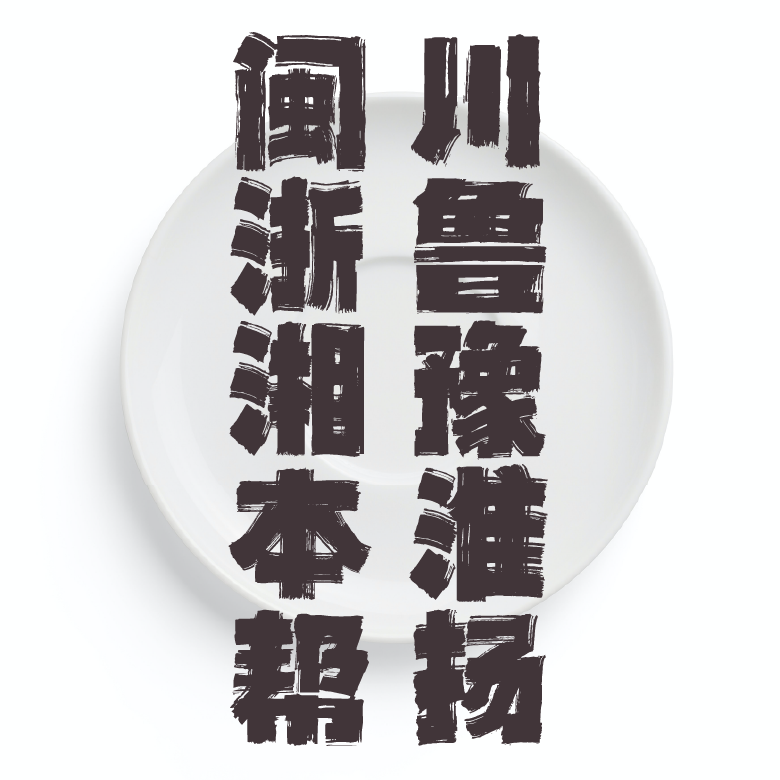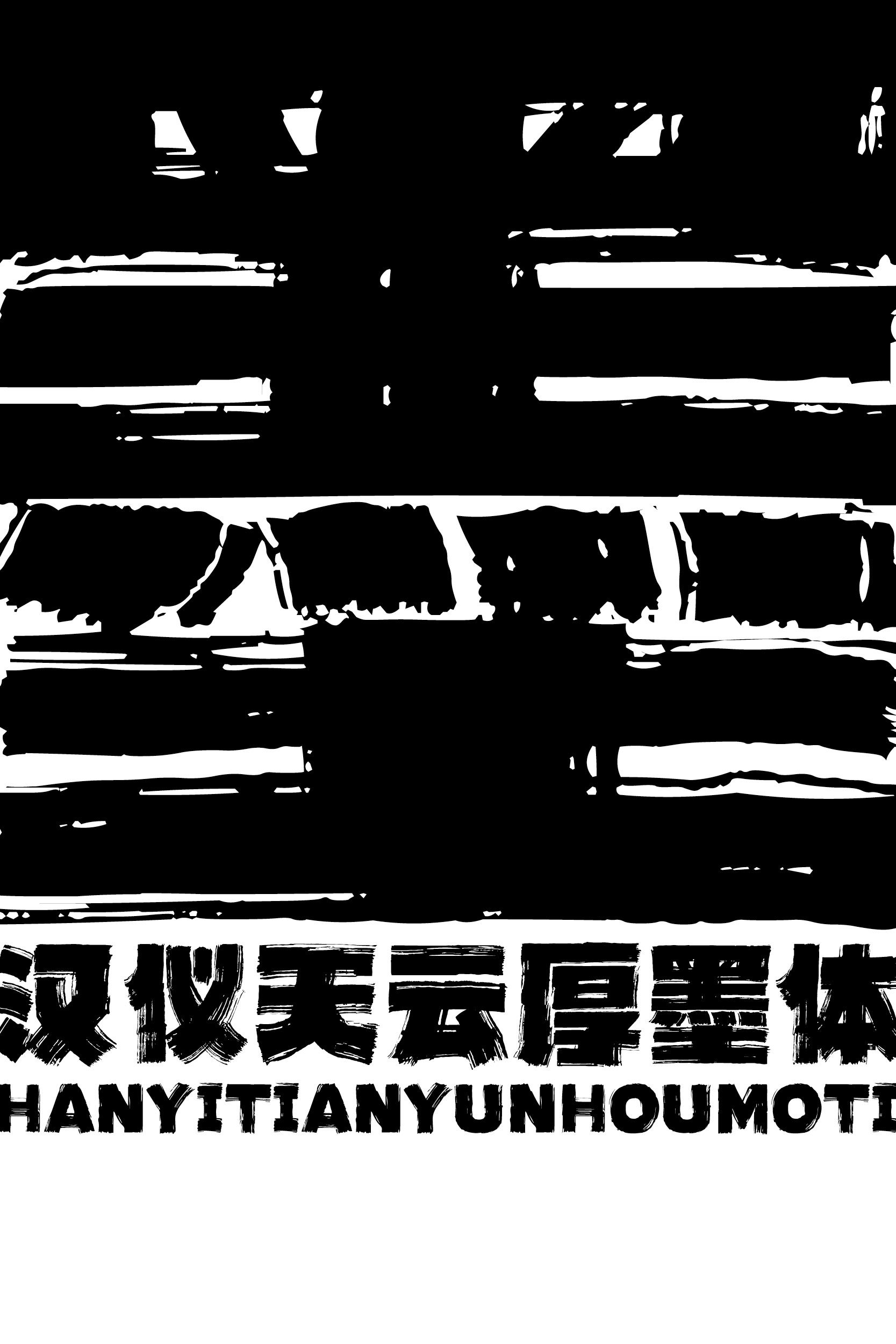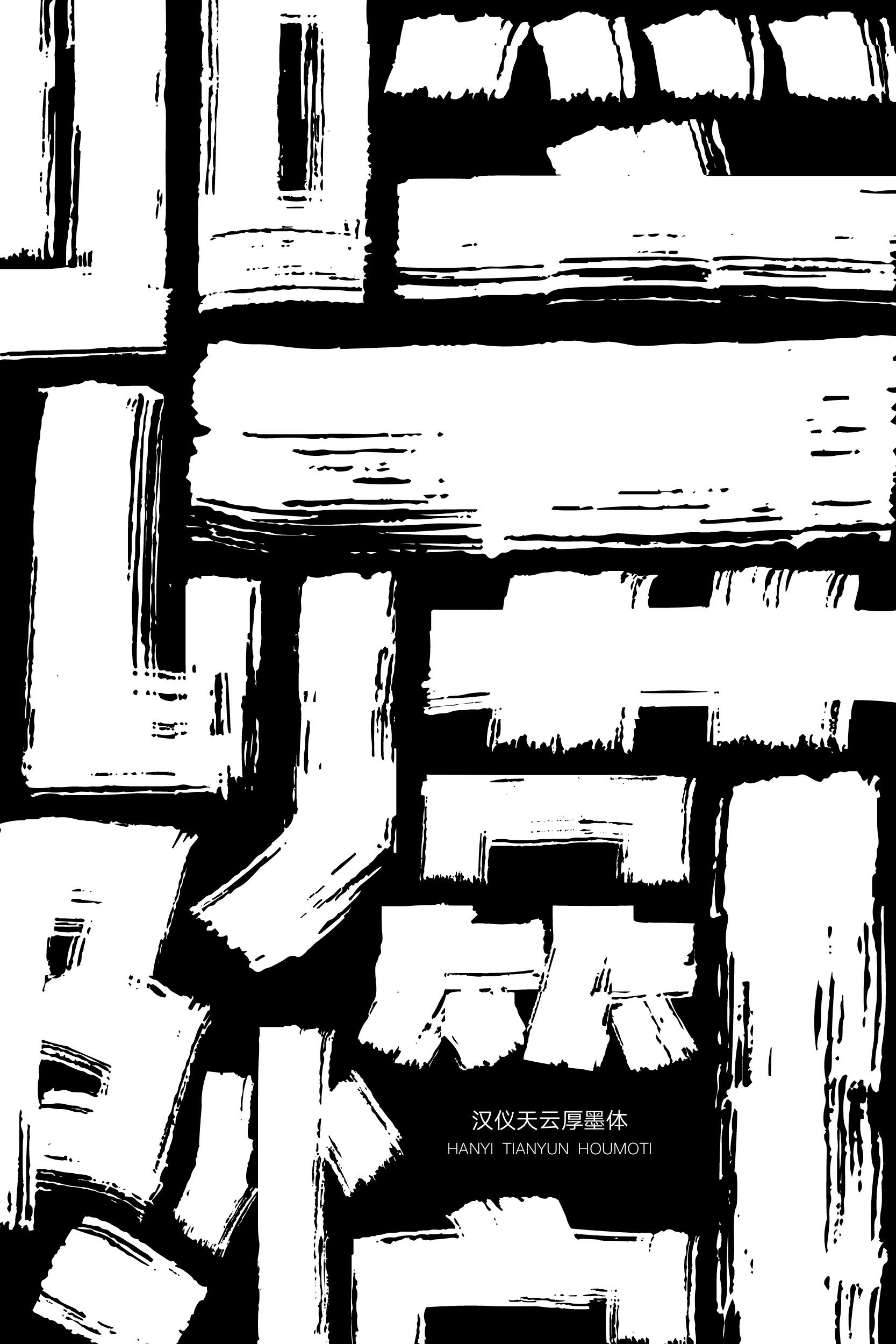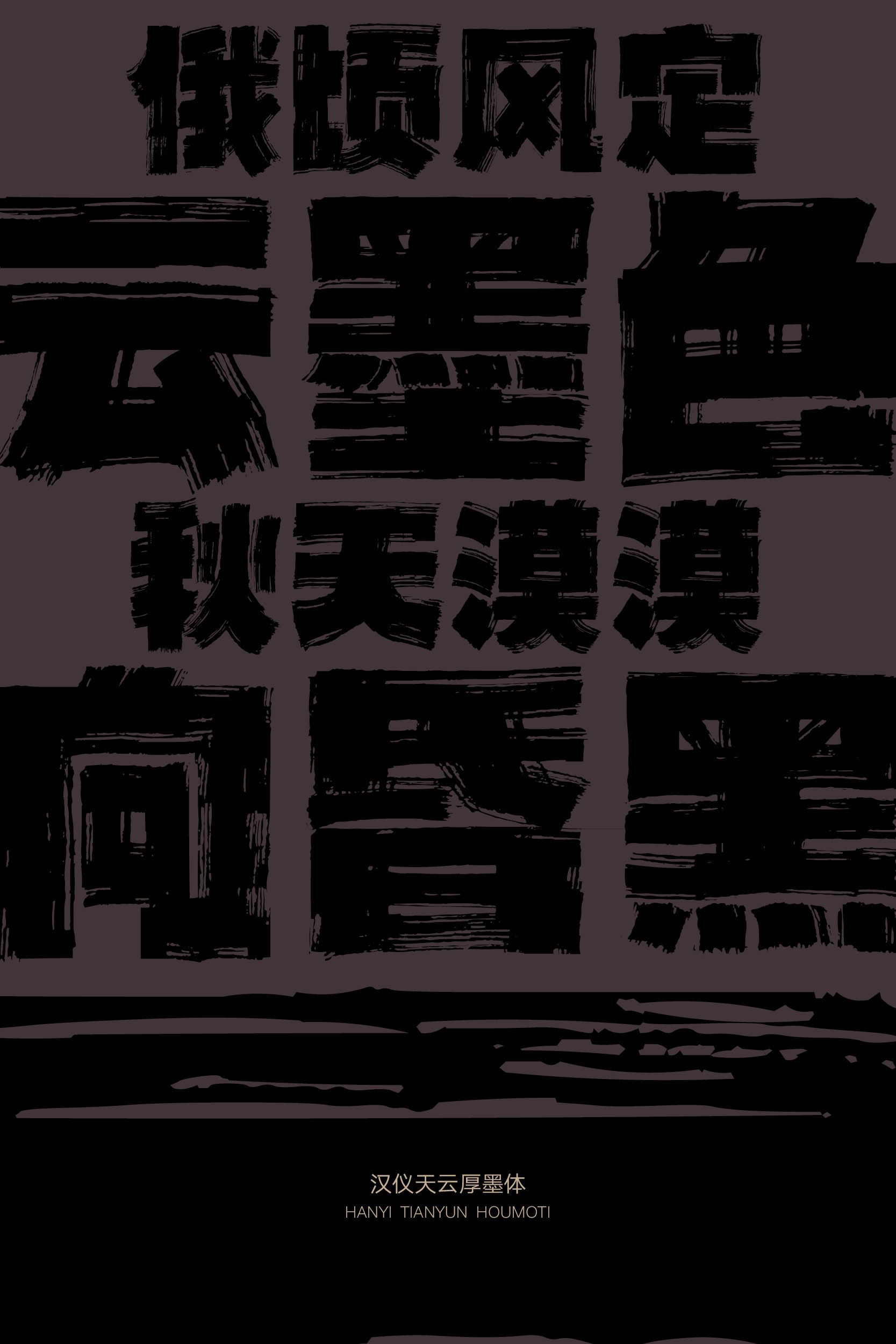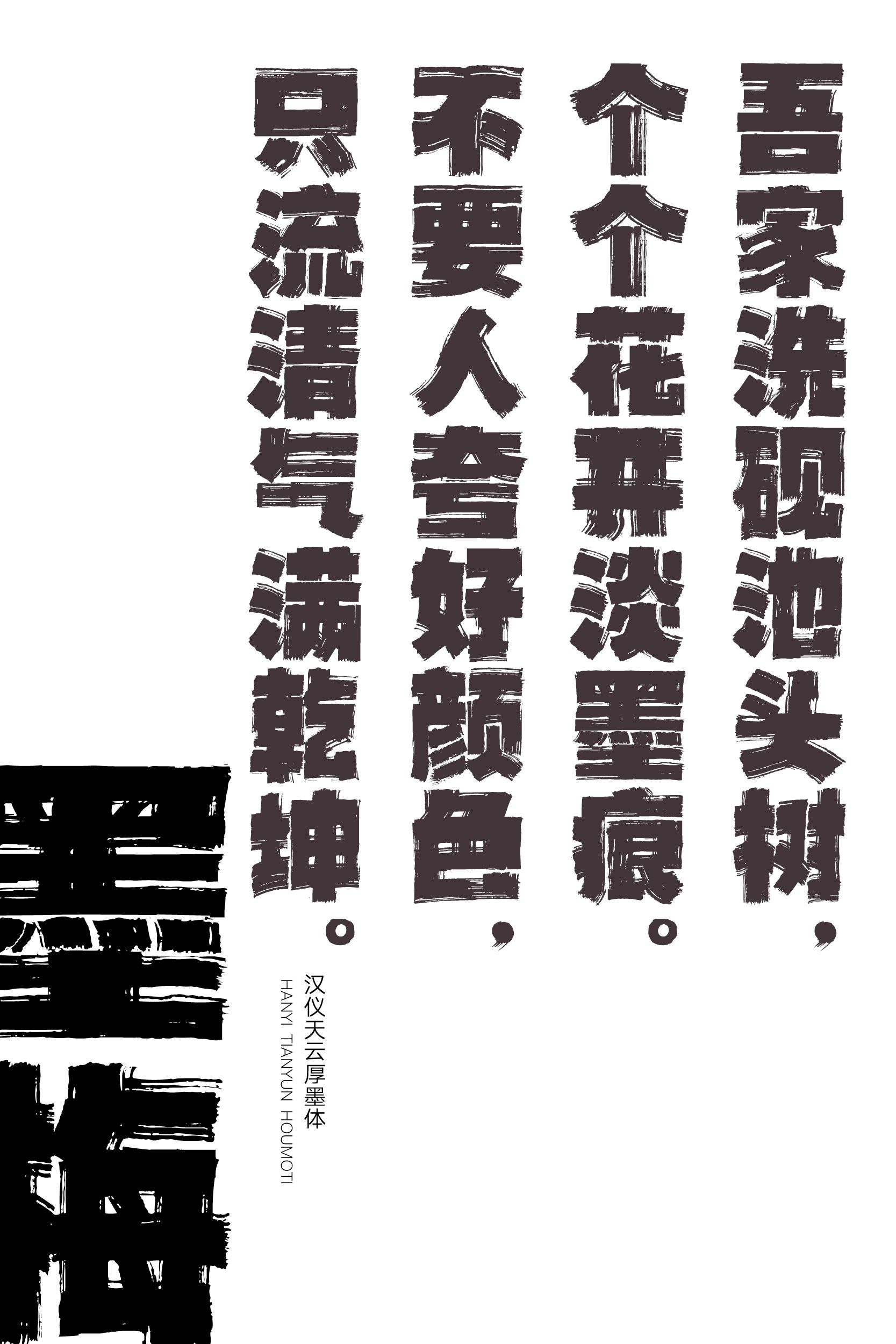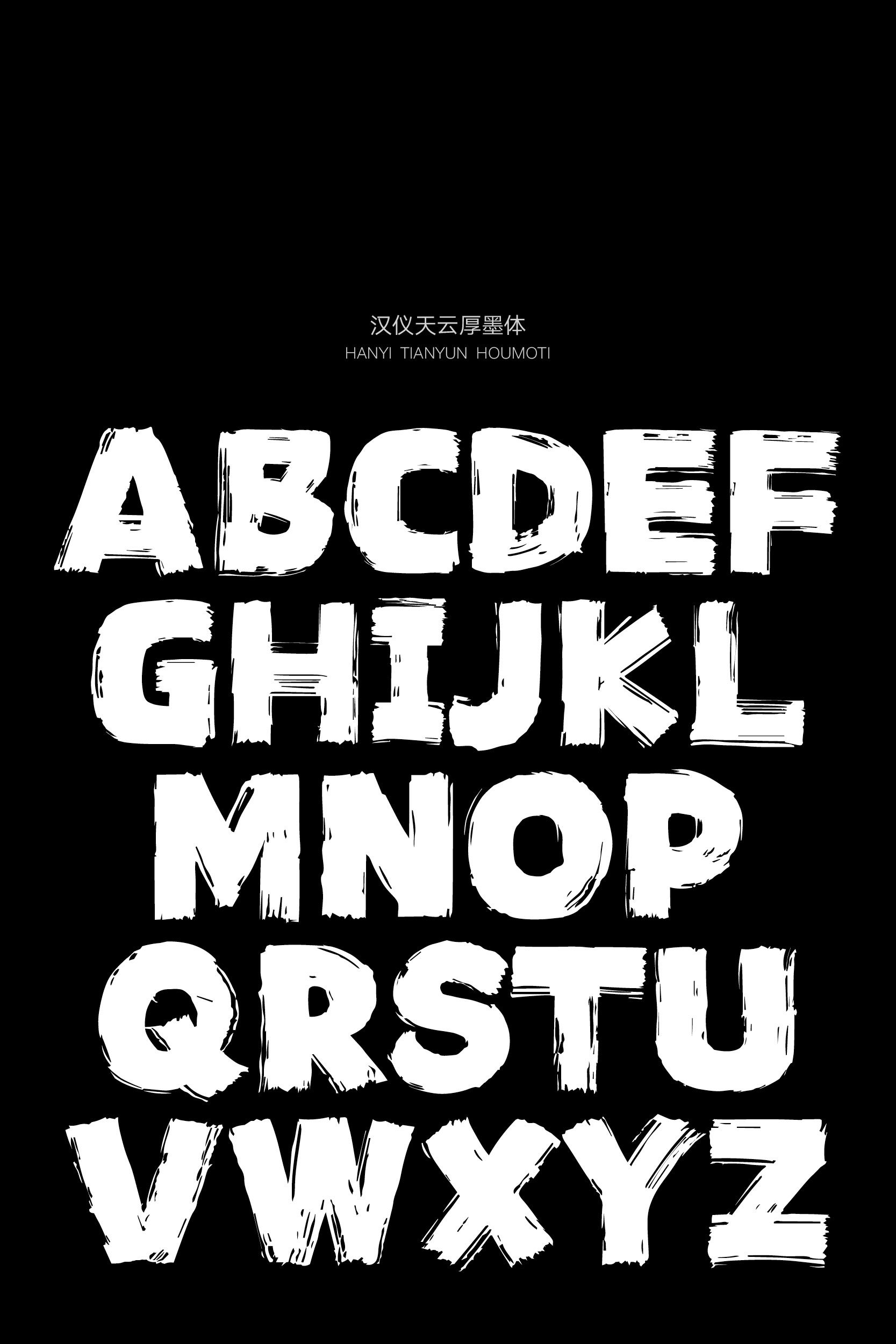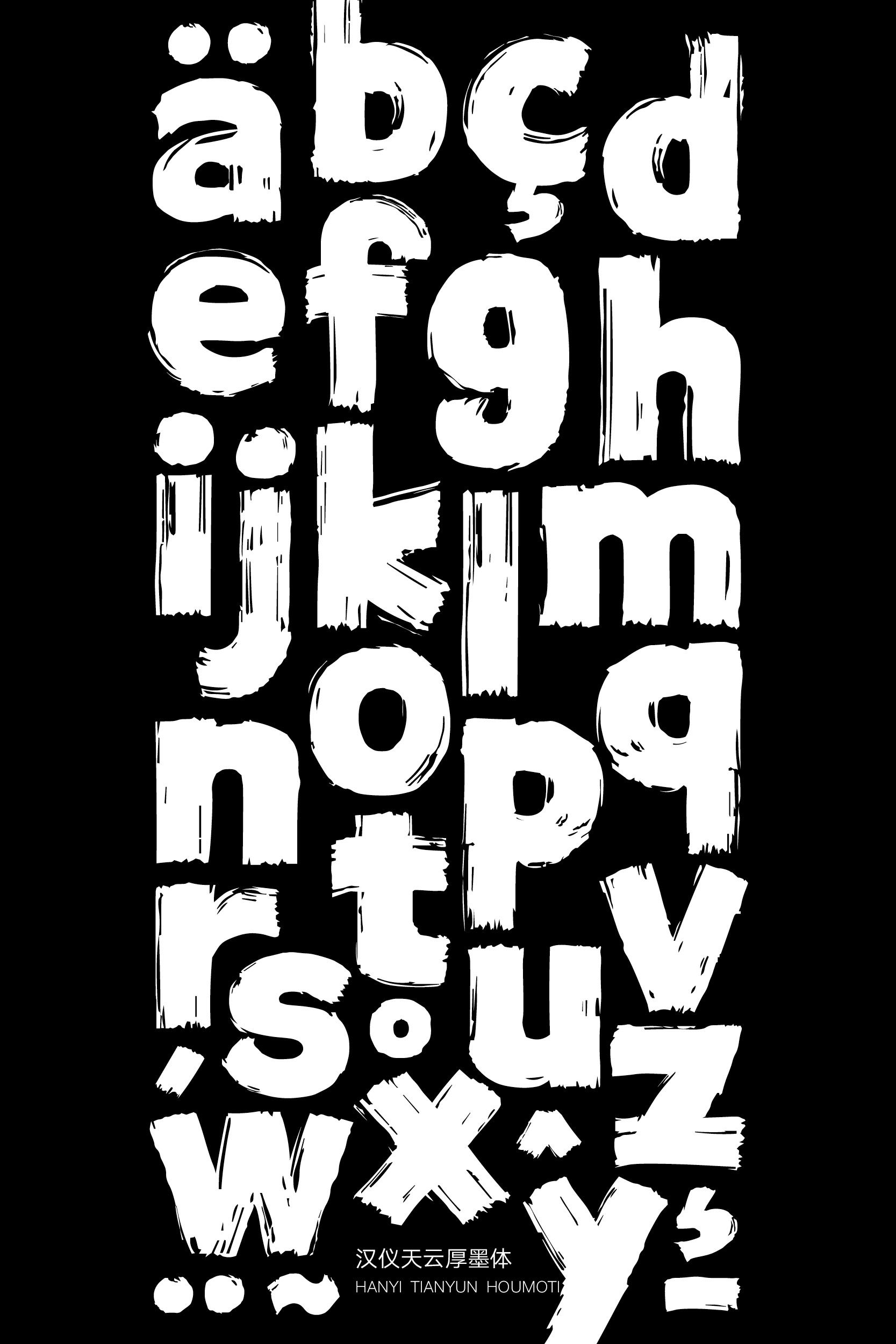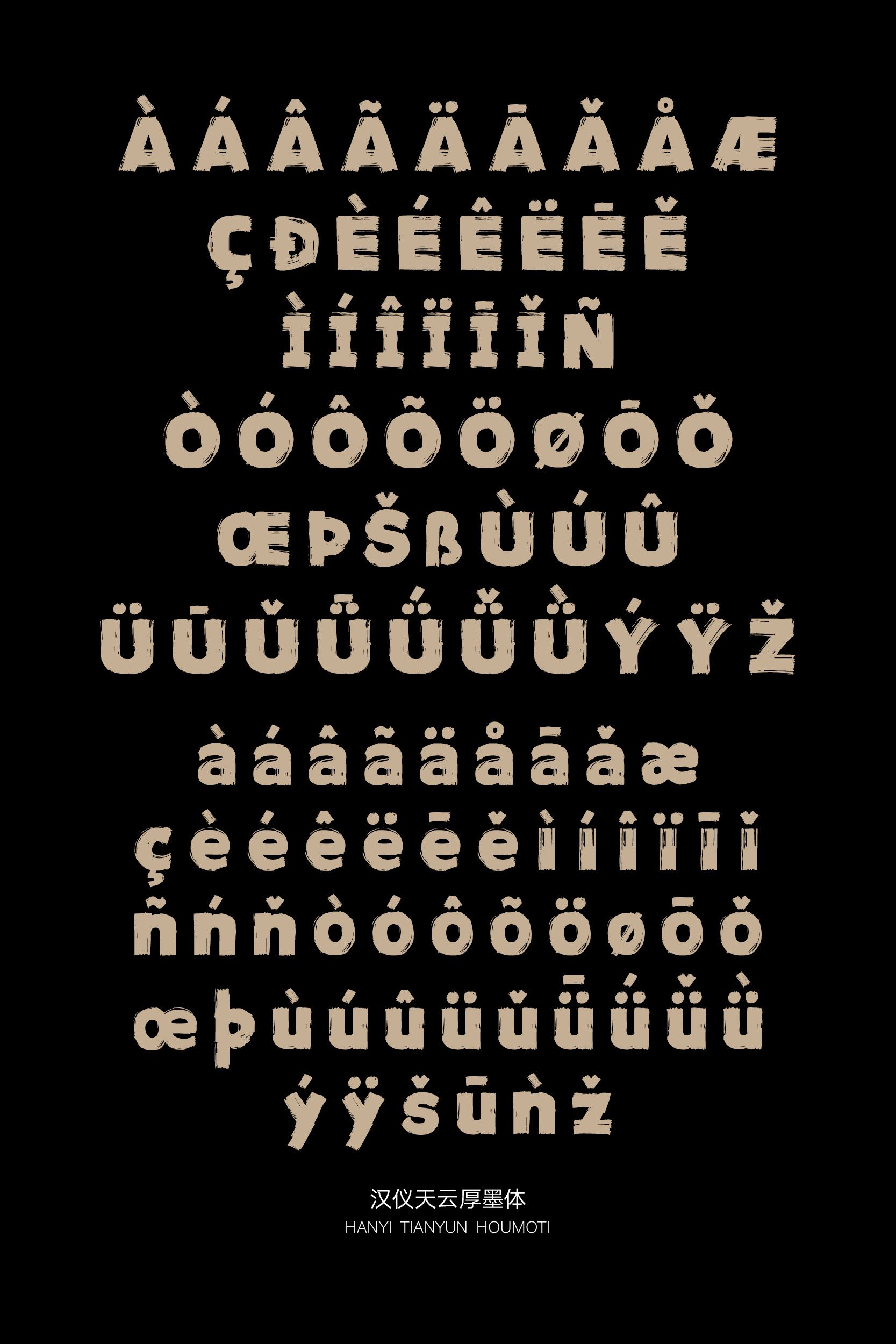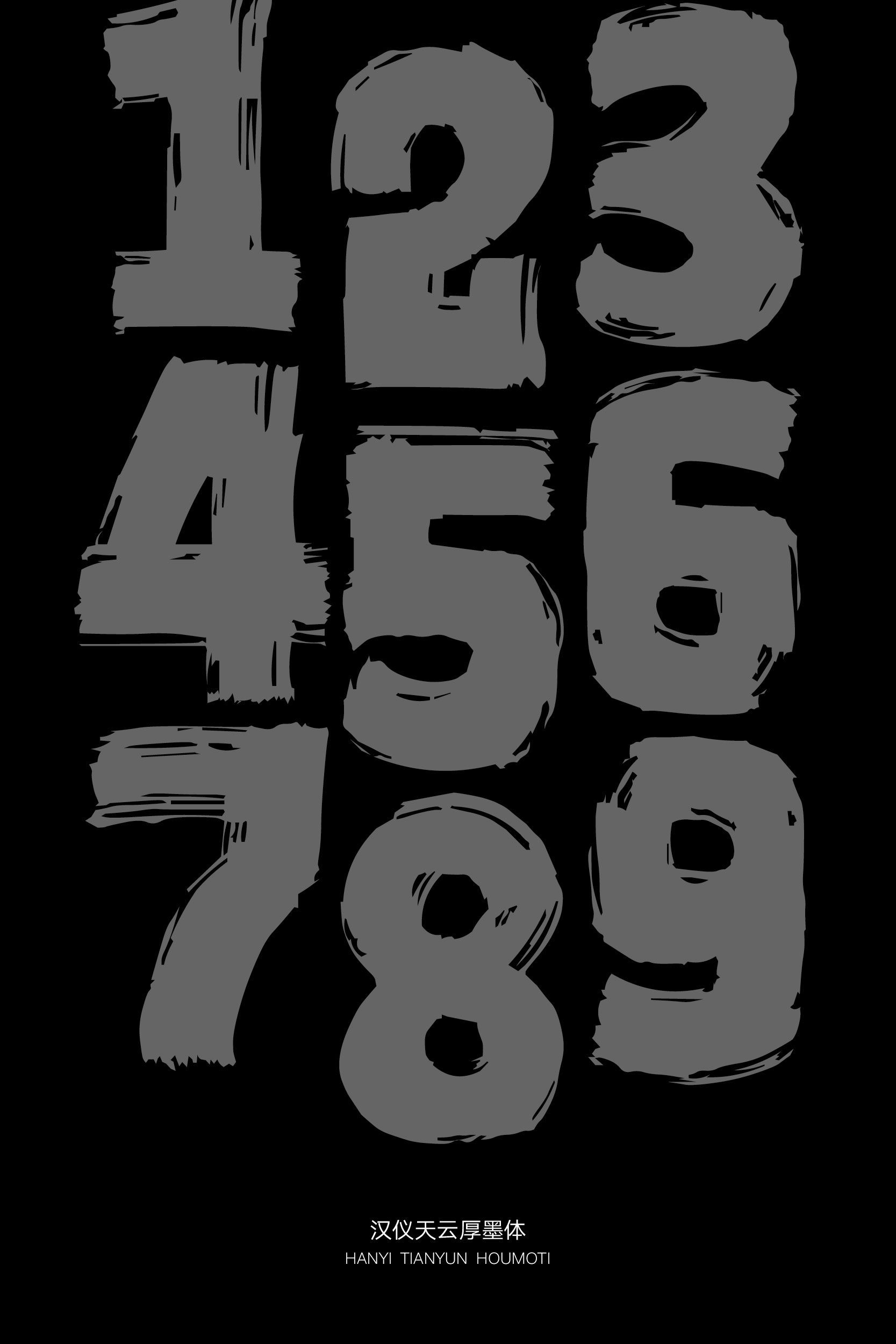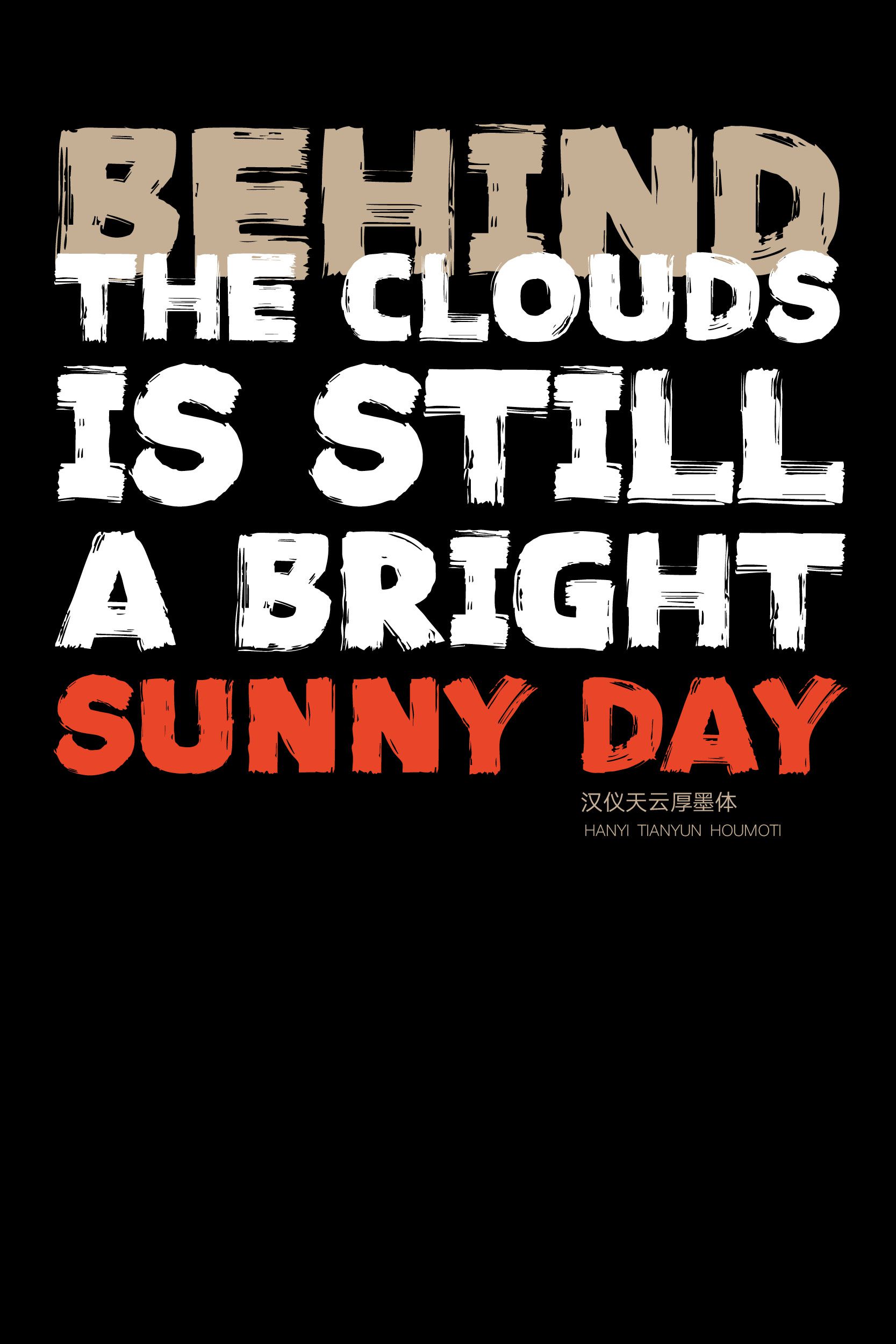
一款力量和人文兼具的书写字体
书写字体
书写 / 浑厚 / 朴茂
标志 / 书籍 / 广告 / 杂志 / 游戏 / 动漫 / 影视 / 包装
汉仪天云厚墨体|浑厚朴茂 天云厚墨
浑厚朴茂的汉仪天云厚墨体是由汉仪字库签约设计师叶秀洪创作的一款极具视觉冲击力的书写字体,由平板笔刷书写绘制而成,方块造型整齐平稳,笔画粗厚,书写的飞白丰富了细节,排版应用的效果如同层云和墨块一般沧桑而通透。这款字体适合作为标题字体使用,既可表现强大的力量感,又能传达人文手写气息,与餐饮、运动、影视等不同类型的场景兼容。
汉仪天云厚墨体|墨块造型 平整苍劲
汉仪天云厚墨体的字形呈整齐平稳的墨块造型,字面阔绰而贴近字面框的边缘,因此具有整体的块面感和苍劲的视觉冲击力。
汉仪天云厚墨体|笔法果敢 飞白酣畅
汉仪天云厚墨体由平板笔刷书写绘制而成,方形的笔画果敢粗厚,笔刷的质感与其形成的不规则边缘使得这款字体具有透气感。
这款字体远看似实心墨块,近看有书写的飞白老练酣畅地运用其中,如层云一般浑厚且通透,如枯墨一般沧桑且朴茂。
汉仪天云厚墨体|中西文匹配
汉仪天云厚墨体的西文设计与中文设计风格一致,字形为整齐的长方形,飞白的处理增添了书写感,中西文搭配和谐统一。
汉仪天云厚墨体|排版应用
汉仪天云厚墨体|样张展示